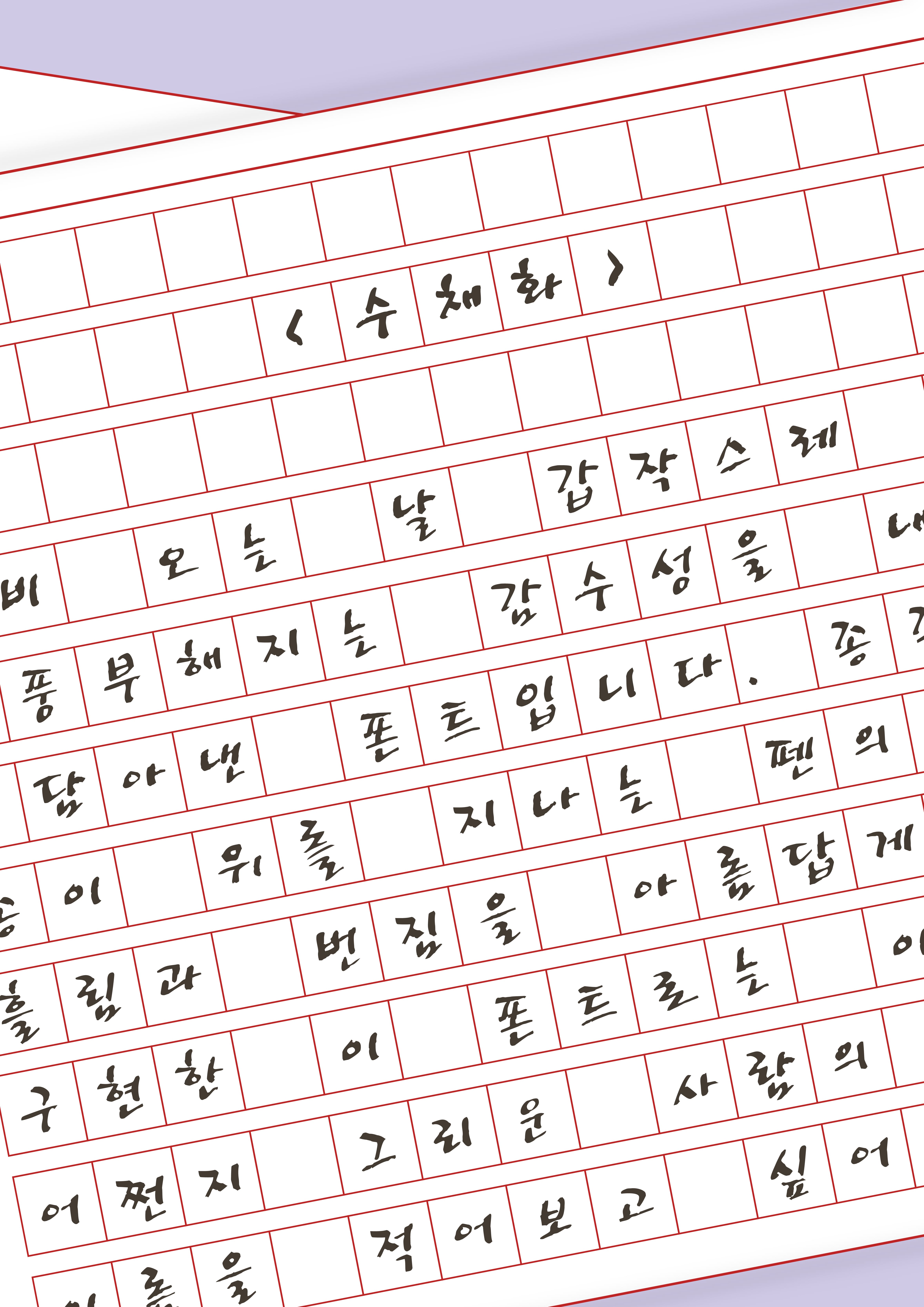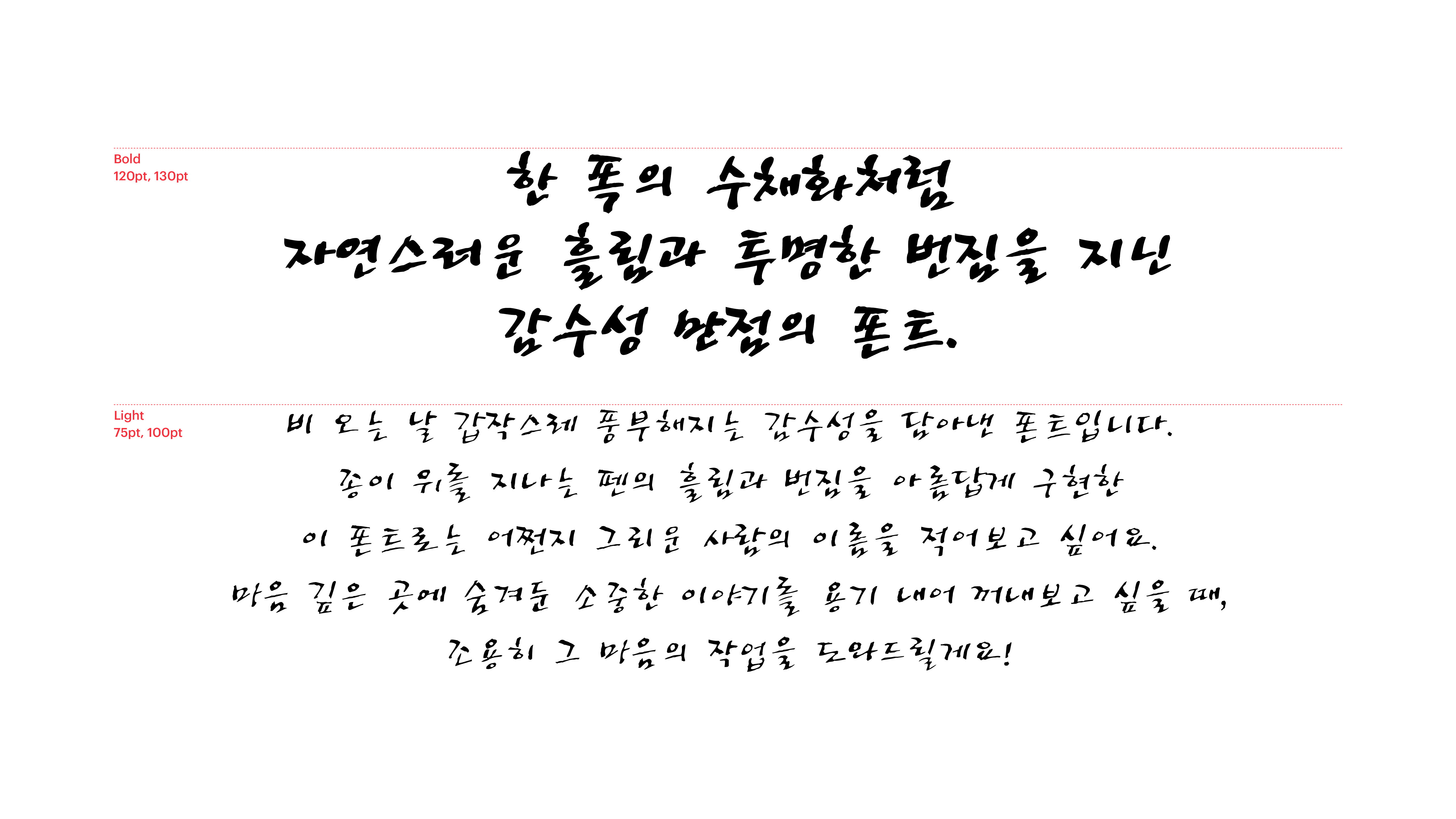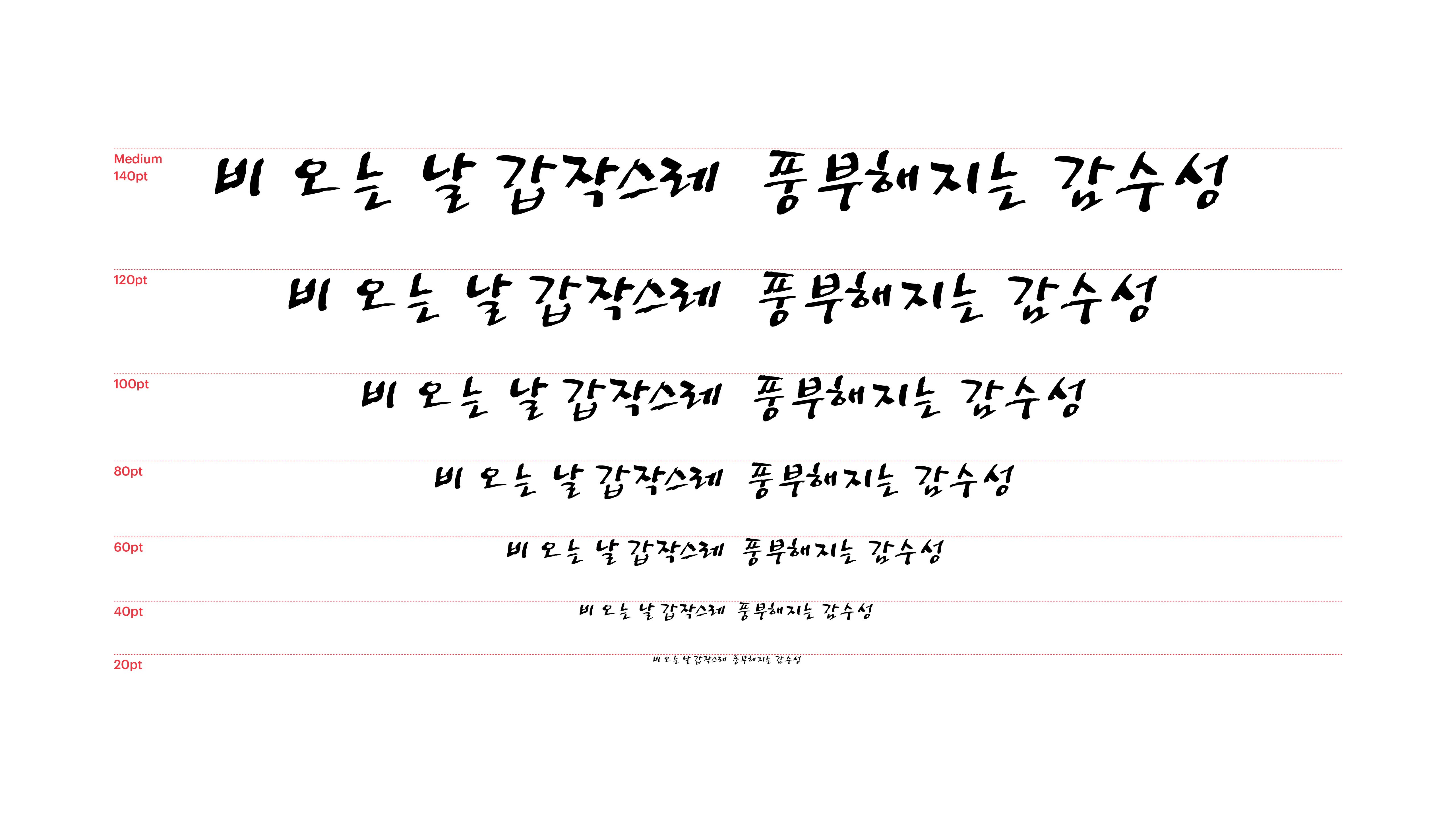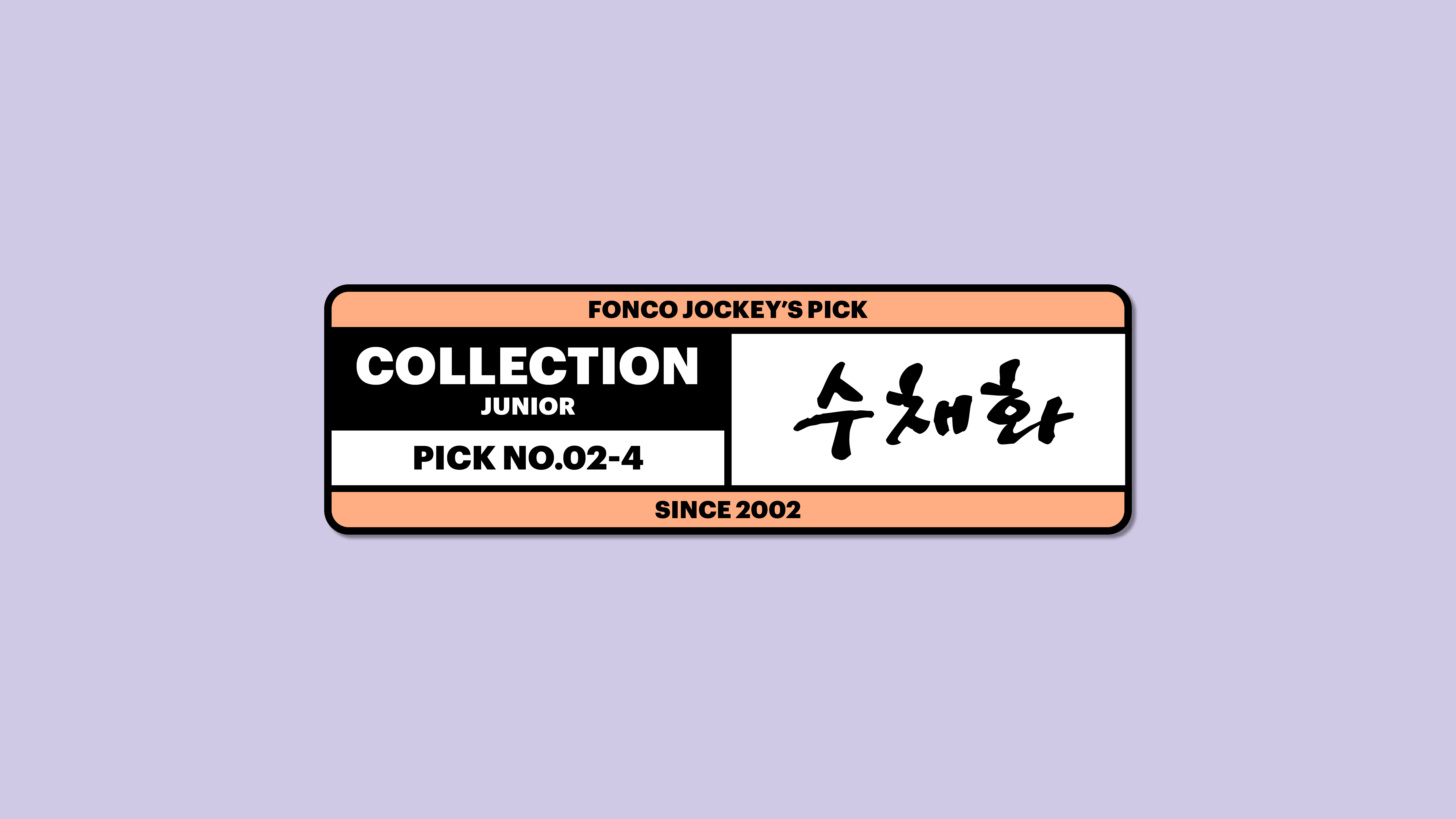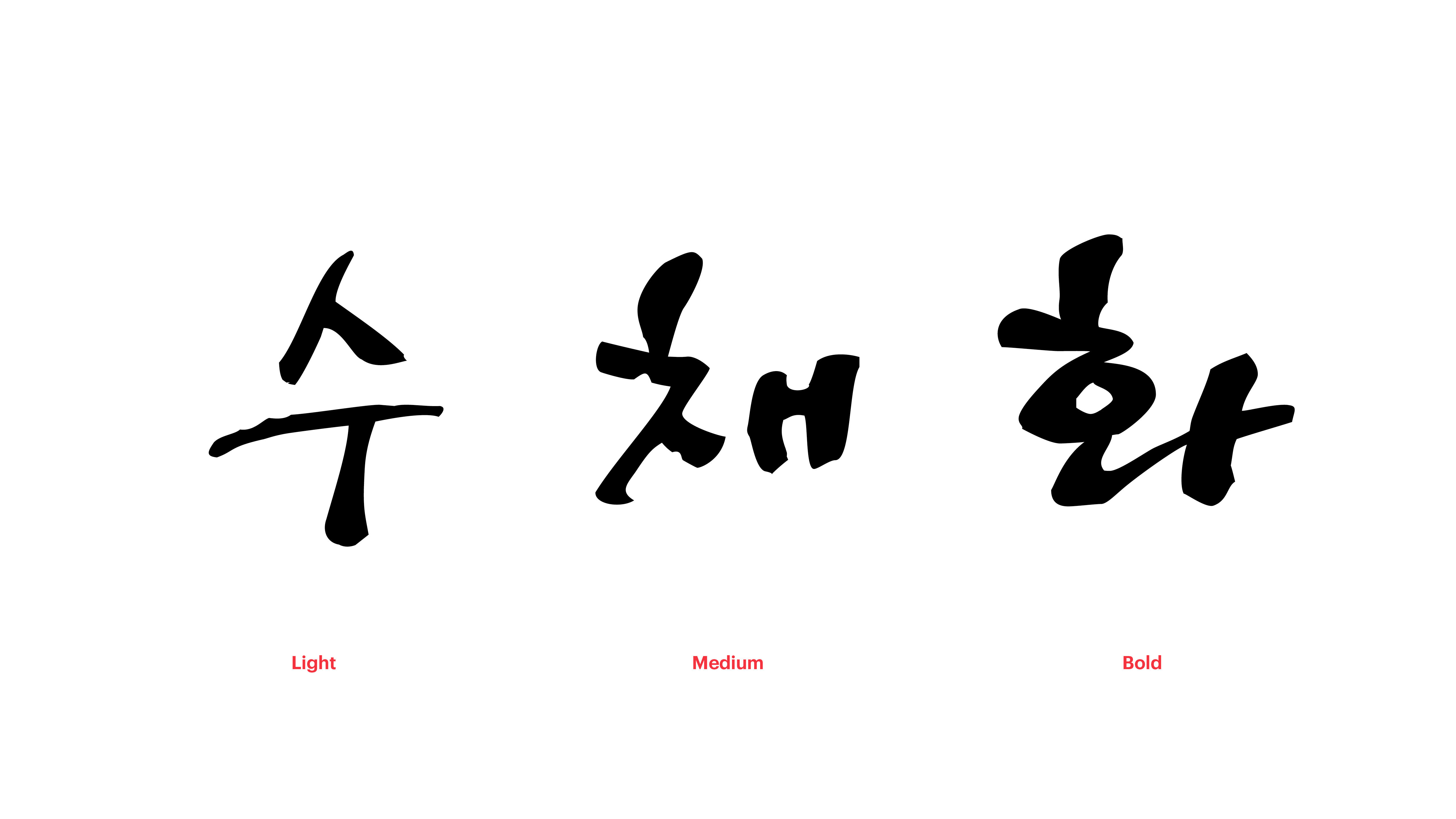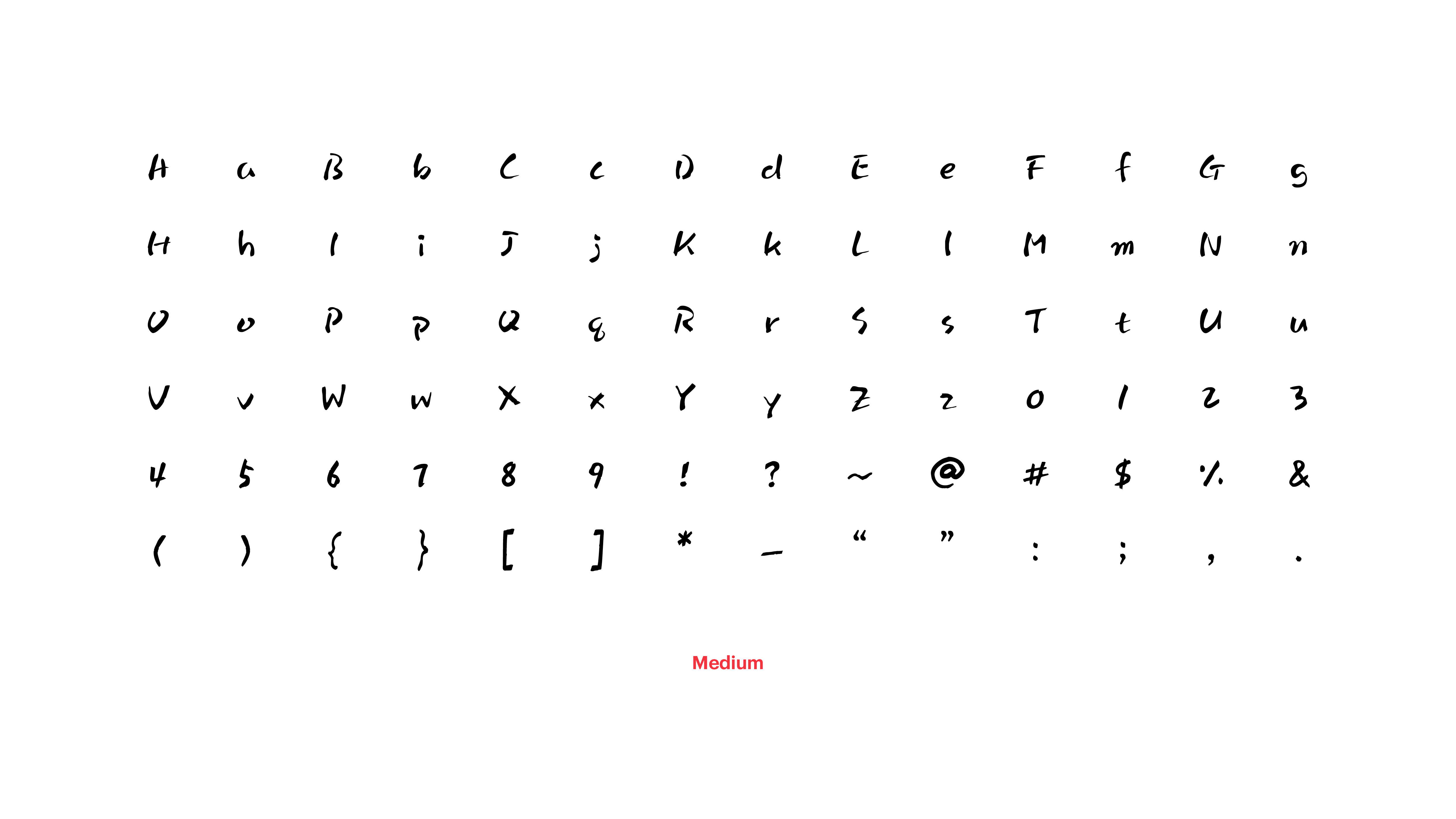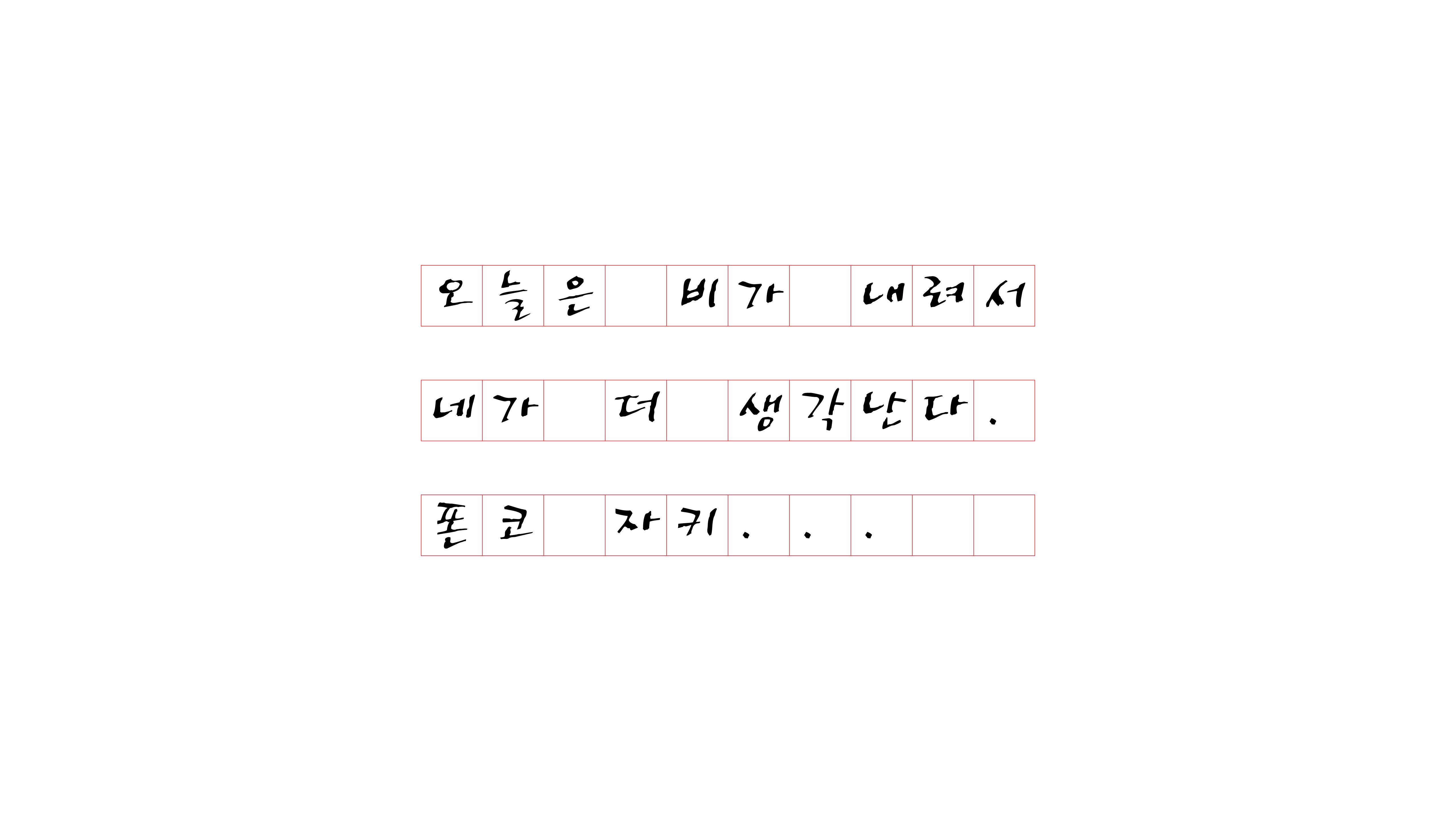
[손글씨]
수채화
2000-2004
Yoon 수채화
비 오는 날 갑작스레 풍부해지는 감수성을 담아낸 폰트입니다. 종이 위를 지나는 펜의 흘림과 번짐을 아름답게 구현한 이 폰트로는 어쩐지 그리운 사람의 이름을 적어보고 싶어요. 마음 깊은 곳에 숨겨둔 소중한 이야기를 용기 내어 꺼내보고 싶을 때, 조용히 그 마음의 작업을 도와드릴게요!